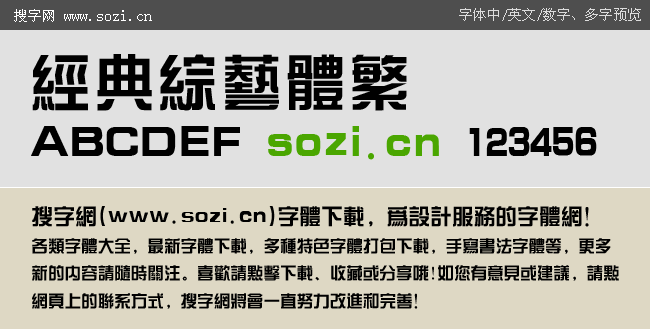
經(jīng)典綜藝體繁
搜字網(wǎng)提供一款經(jīng)典綜藝體繁下載。綜藝體是黑體的一種變體,也是藝術(shù)字的一種。特點(diǎn)是筆劃更粗,盡量將空間充滿。同時(shí)為了美觀,對(duì)拐彎處的處理較為圓潤(rùn)。適用于廣告、報(bào)刊等的標(biāo)題及海報(bào)展板等設(shè)計(jì)場(chǎng)合使用。